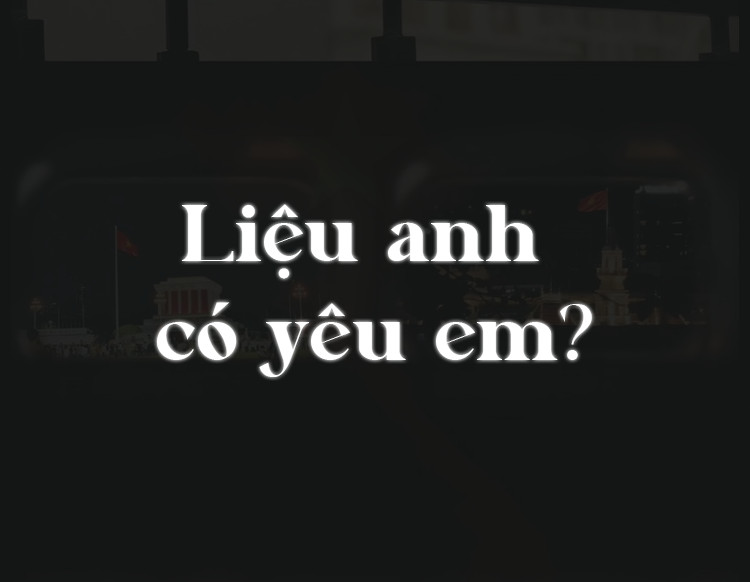
Giới thiệu về Font việt hoá MJ Brave Paridos
Trong thế giới đồ họa hiện đại, việc lựa chọn Font Chữ phù hợp đóng vai trò quyết định đến tính thẩm mỹ của sản phẩm. Font việt hoá MJ Brave Paridos là một bộ phông chữ mang phong cách mạnh mẽ, cá tính nhưng không kém phần tinh tế. Đây là lựa chọn hoàn hảo cho các bạn học sinh và giáo viên khi muốn tạo ra những bài thuyết trình hay báo cáo ấn tượng. Với đường nét sắc sảo và bố cục cân đối, bộ font này giúp thông điệp truyền tải trở nên chuyên nghiệp và dễ tiếp cận hơn đối với người xem.
Đặc điểm nổi bật của Font việt hoá MJ Brave Paridos
Bộ phông này nổi bật nhờ khả năng hiển thị tiếng Việt trọn vẹn, không bị lỗi dấu – một vấn đề thường gặp ở các font ngoại nhập. Font việt hoá MJ Brave Paridos hỗ trợ đầy đủ các ký tự đặc trưng, giúp người dùng tự tin sáng tạo trên các phần mềm như Word, PowerPoint hay Photoshop. Ngoài ra, phong cách thiết kế hiện đại của nó rất phù hợp cho các tiêu đề lớn, banner sự kiện trường học hoặc các dự án truyền thông sáng tạo đòi hỏi sự phá cách.
Cách sử dụng và cài đặt hiệu quả
Để tận dụng tối đa vẻ đẹp của phông chữ này, bạn nên kết hợp nó với các màu sắc tương phản để làm nổi bật tiêu đề. Việc cài đặt cũng rất đơn giản, chỉ cần tải tệp về và cài vào thư mục font của máy tính. Font việt hoá MJ Brave Paridos không chỉ là một công cụ trang trí mà còn là nguồn cảm hứng giúp các em học sinh yêu thích hơn việc trình bày nội dung số một cách khoa học và đẹp mắt.